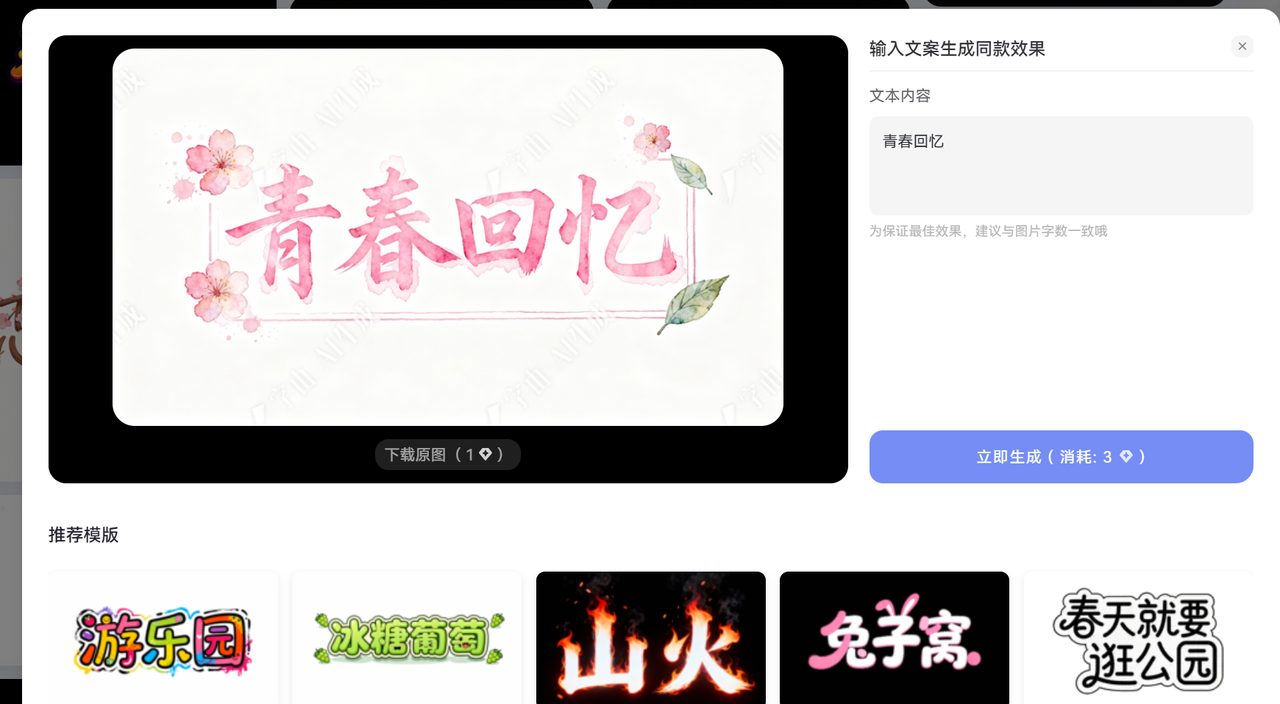
如何制作特效字体,分享 5 款好用的特效字体制作工具
你是不是也想把平平无奇的文字变成火焰字、冰晶字、霓虹字、金属字,甚至是3D立体字,但是不知道如果制作或者制作成本太高?
今天我就来给大家盘点几款我个人觉得超级好用、功能强大的特效字体制作工具。无论你是设计小白,还是有一定基础的进阶用户,都能快速生成你想要的特效字体。
字由 AI 字体
字由 AI 字体是一款简单好用的特效字体制作工具,无需专业的设计经验,就可以快速的生成想要的特效字体。
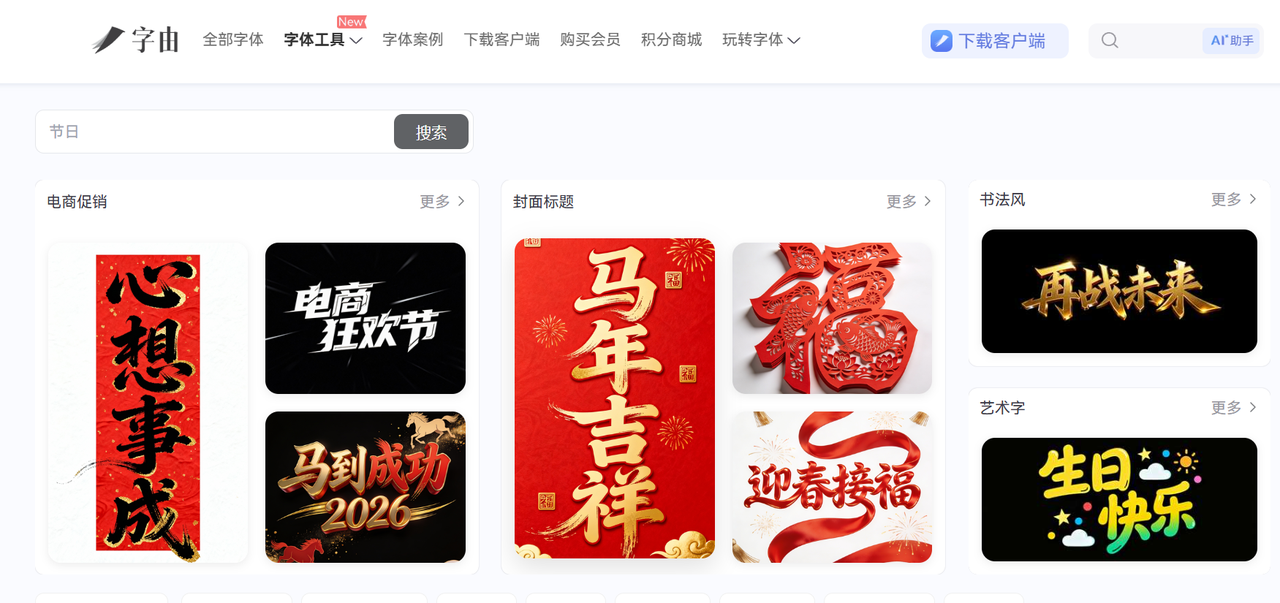
平台根据不同的使用场景和风格,提供了非常丰富的字体模板。
根据你想要的特效字体的使用场景和风格,筛选符合的特效模板,然后点击“做同款”,最后输入自己的文案即可。
Flaming Text
比较老牌的在线文字Logo生成器。它们不像Canva或Photoshop那样是全面的设计工具,而是专注于提供大量预设的文字样式和效果,让你能以最快的速度生成一个带有特殊效果的文字图片。它们的操作非常简单,无需注册,打开网页就能用,非常适合那些只需要一个简单、快速、即时效果的场景。
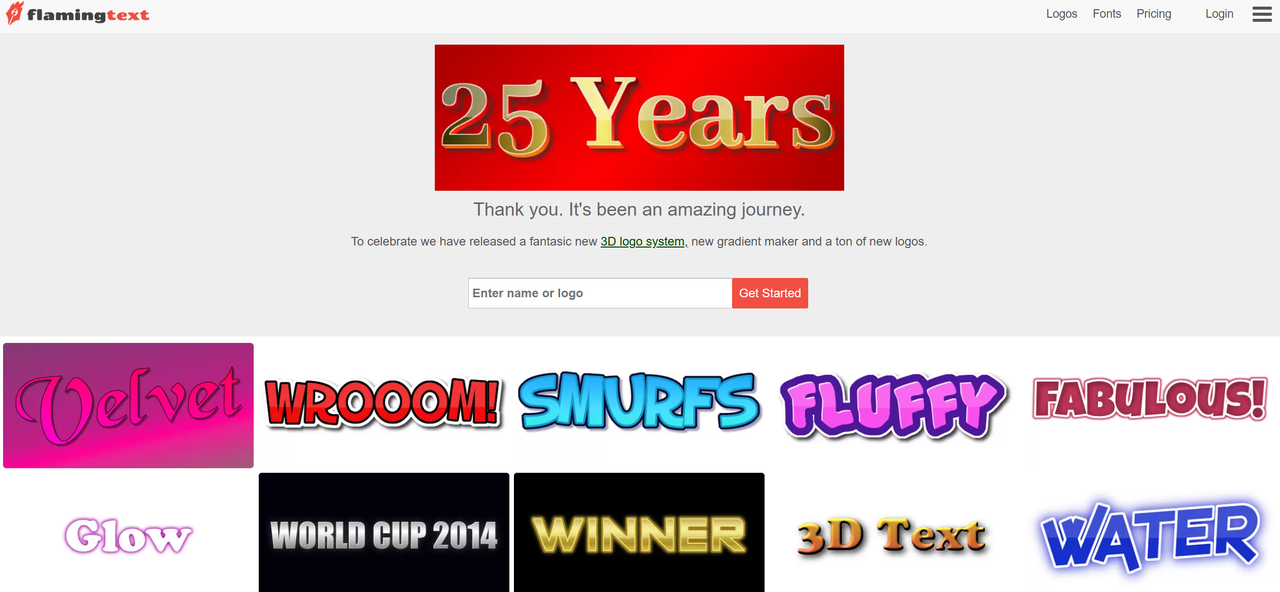
- 核心优势就是速度!你只需输入文字,选择一个喜欢的预设样式,几秒钟内就能看到效果并下载。
- 提供了各种经典和流行的文字效果,如火焰字、冰晶字、金属字、霓虹字、卡通字、像素字、涂鸦字等。每种样式都有不同的字体和颜色组合。
- 虽然是预设样式,但通常也允许你对字体、字号、颜色、背景、阴影等进行一些基础的自定义调整,以满足你的特定需求。
- 缺点是自定义程度相对较低,特效样式也相对固定,难以创造出独一无二的复杂效果。
Canva
Canva是一款非常流行的在线图形设计工具,它以其超高的易用性和丰富的模板资源,受到了全球数千万用户的喜爱。虽然它不是一个纯粹的“字体生成器”,但它在文字处理和特效应用方面的能力,绝对能满足绝大多数人的需求。你可以把它想象成一个包含了无数设计元素的“创意乐高”,文字只是其中一个重要的组成部分。它的界面直观,操作简单,哪怕你是第一次接触设计软件,也能很快上手,做出令人惊艳的作品。
- Canva内置了成千上万种字体,包括各种风格、语言的字体,让你永远不愁找不到合适的字体。
- 你可以轻松为文字添加阴影、描边、霓虹灯光、故障艺术(Glitch)、曲线、镂空、渐变等多种特效。这些特效都是一键应用,还能进行细致的参数调整,比如阴影的距离、模糊度、颜色,描边的粗细、颜色等等。
- Canva还支持为文字添加各种动态入场和出场动画,让你的标题或短句在视频或演示文稿中动起来,更具吸引力。
Fotor
Fotor是一款功能强大的在线图片编辑器和平面设计工具,和 Canva 类似,它在文字处理和特效方面同样表现出色,Fotor的界面设计也很友好,功能模块清晰,让你在处理图片的同时,也能轻松为文字增添光彩。
- Fotor提供了丰富的预设文字样式,包括各种字体、颜色、大小和排版组合,让你快速找到灵感。
- 你可以为文字添加阴影、发光、描边、纹理填充等多种特效。比如,你可以让文字呈现出金属拉丝的质感,或者像水面一样波光粼粼。这些特效的参数都可以进行精细调整,满足你的个性化需求。
- Fotor允许你将文字与各种图形、图标结合,创造出独特的文字Logo或标题设计。它还有一些独特的文字扭曲和变形工具,让文字更具艺术感。
PS 为什么不建议
当然,PS 是可以实现的,提到图像处理和平面设计,就不得不提Adobe Photoshop。Photoshop在文字处理和特效生成方面的能力,可以说达到了炉火纯青的地步,几乎没有它做不到的文字效果。如果你追求极致的细节、无限的创意和专业的输出质量,并且愿意投入时间和精力去学习,那么Photoshop绝对是你的不二之选。
- 从最基本的字体、字号、字距、行距,到高级的OpenType字体特性、连字、替代字符等,Photoshop提供了最全面的文字排版控制。
- Photoshop内置强大的3D功能,可以将平面文字直接转换为3D对象,并为其添加各种材质(如玻璃、金属、木头)、灯光、阴影和纹理。
- 结合Photoshop庞大的滤镜库(如扭曲、渲染、模糊等)和各种调整图层,你可以对文字特效进行深度加工,实现更具艺术性和个性化的效果。
- Photoshop的缺点在于它的学习成本和制作成本都比较高,不适合新手和非专业人员。